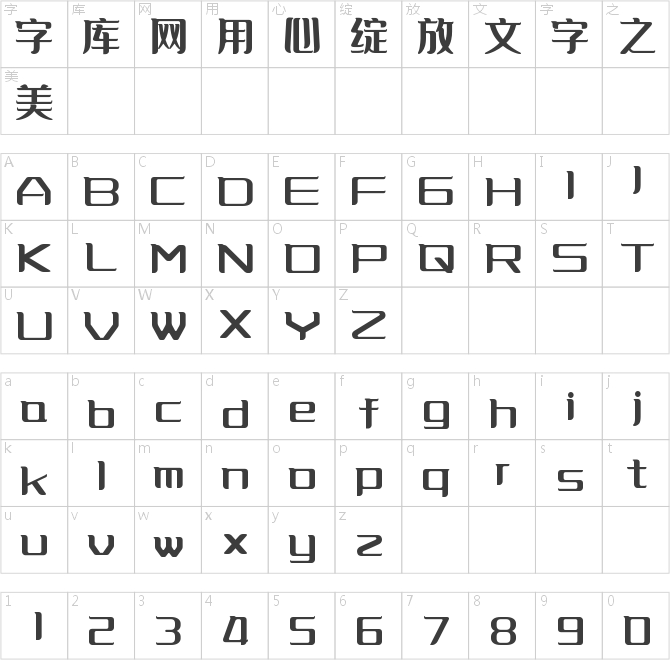
字魂184號-銀翼創(chuàng)世黑
字魂184號-銀翼創(chuàng)世黑字體zihun184hao-yinyichuangshihei字庫是一款讓人賞心悅目、百看不厭的中文字體,適合各類廣告和產品包裝設計應用,字體大小3.86MB,格式為ttf字體,上傳用戶是ㄚòひ慬偶鰢,作者/版權方為字魂